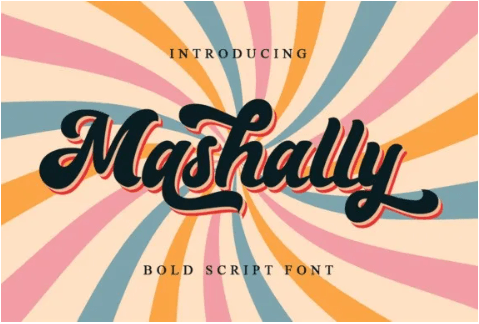
Шрифт Машаллы
Mashally Font
Mashally — великолепный рукописный шрифт, вдохновленный винтажной каллиграфией. Он отлично подходит для приглашений, дизайнов футболок, надписей, цитат, поздравительных открыток и многого другого! Mashally идеально подходит для тех, кто хочет, чтобы их работа, проекты и записи выглядели более естественно и лично.